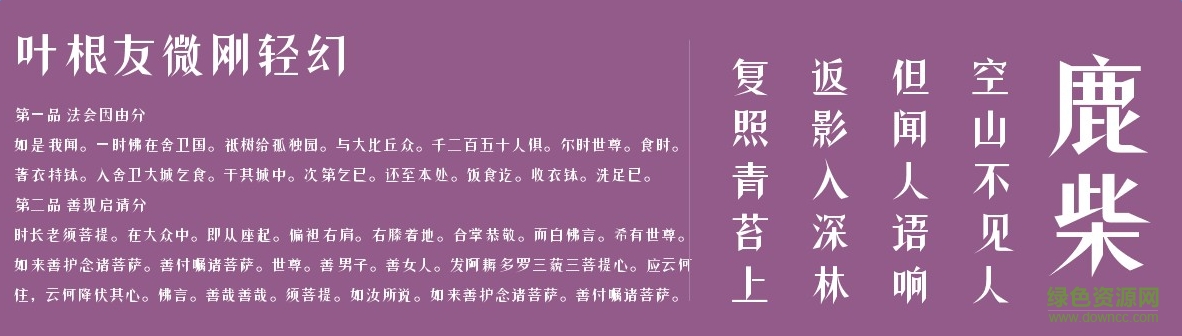
葉根友微剛輕幻字體是一款由知名書(shū)法家葉根友創(chuàng)造的字體,比劃圓潤(rùn),適用于廣告、藝術(shù)設(shè)計(jì),海報(bào)設(shè)計(jì)等方面,有需要的朋友們不要錯(cuò)過(guò)了。歡迎大家來(lái)綠色資源網(wǎng)踴躍下載哦!
葉根友微剛輕幻字體是一款柔性的字體,比較適合內(nèi)文排版和追求時(shí)尚一族的應(yīng)用,字體空靈輕快秀麗。
葉根友微剛輕幻字體,用途廣泛,是葉根友先生的印刷字體,字體看起來(lái)柔美,沒(méi)有太多的剛性,非常舒服。各位字體收藏者可以來(lái)看看。